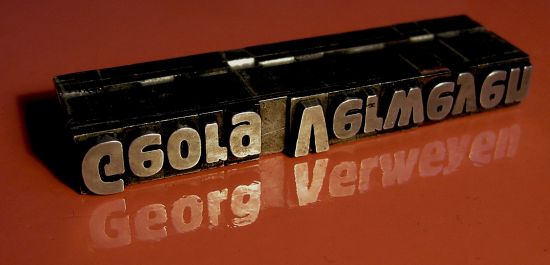
Ich bin Studentin und muss nächste Woche ein Referat über Herrn Renners "Futura" halten. Bei meinen Recherchen habe ich herrausgefunden, dass die Futura das Skelett einer Antiqua hat. Mich würde jetzt brennent interessieren, welche Antiqua damals als Parte gedient hat.
Über Links zum Thema Futura und Paul Renner würde ich mich auch freuen. Vielleicht weiß ja noch jemand was, was ich nicht weiß.
Ergänze doch einmal bitte jemand die CI-Liste:
Nicht nur Volkswagen und Ikea nutzen die Futura oder deren Varianten, sondern immerhin seit Beginn des Jahres 2007 auch als fast-amtiliche Stelle das Preußische Bleisatz-Magazin - seit Jahren Anlaufstelle für ver(w)irrte weibliche Jungsemester, die einen Ausflug in die Welt der sabbernden Altherren-Bleisetzer nicht scheuen, um deren Futura-Bestände sachte in Händen zu wiegen.
... das Preußische Bleisatz-Magazin - seit Jahren Anlaufstelle für ver(w)irrte weibliche Jungsemester, die einen Ausflug in die Welt der sabbernden Altherren-Bleisetzer nicht scheuen, um deren Futura-Bestände sachte in Händen zu wiegen.
Es sollen sich auch schon jung-schnöselige Streberlinge mit dem Fahrrad dorthin verirrt haben, die reich beschenkt und mit Blei unter den Fingernägeln zurückgekehrt sind.
Neben einem Wohnzimmertischchen in undefinierbarer Farbe, einer Schreibtischlampe für die Ausleuchtung, einer Kamera mit Stativ und etwas Geduld braucht man vor allem eine schön glänzende Block. Immerhin feiert das durchaus noch zeitgemäße Schätzchen nächstes Jahr seinen hundertsten Geburtstag, da ist ein glänzender Auftritt mehr als verdient (ja, auch hier, wie bei der Helvetica, kam viel Antimon zum Einsatz, so habe ich gelernt).
Für das Bild hätte man sich in Photoshop ganz schön den Mausfinger wundgeklickt – manchmal muss es eben echtes Blei sein.
Mh, also ihr meint die Antiqua, war die Capitalis Monomentalis???? Aber das ist ja keine Antiqua... Sondern Versalien. Also es ging ja eher um die Proportionen. Denn die Futura ist zwar konstruiert, orientiert sich aber eben an den Proportionen einer Antiqua. Aber ist das jetzt eine spezielle? Oder verschiedene?? Wenn es eine Spezielle Antiqua gäbe, wäre das ja für mein Referat ganz interessant, diese zu zeigen...
ich werde mal weiter recherchieren. Kann mir irgendwer nen gutes Buch zu dem Thema empfehlen? Ich kenne von Renner selber Kulturbolschewismus und die Kunst der Typografie.
Ach irgenwie hatte ich mir das einfach vorgestellt, was über Renners Schriften und ihre Entstehung zu erfahren. Ich mein, dass ist doch voll der Hit diese Schrift... grr.
Kann mir irgendwer nen gutes Buch zu dem Thema empfehlen? Ich kenne von Renner selber Kulturbolschewismus und die Kunst der Typografie.
Das ist das Standardwerk zum Thema, das ich wärmstens empfehlen kann.